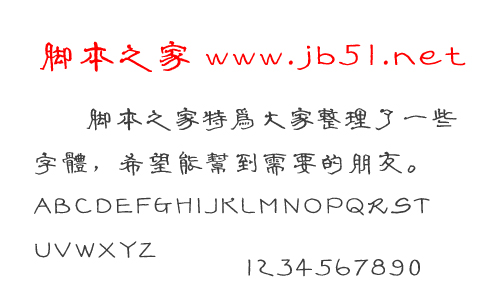
騰祥铚謙隸書繁是作者高铚謙先生撰寫的書法體字庫,整幅字體風格統(tǒng)一、行文規(guī)整,以清朝隸書大家的書法風格為創(chuàng)作源泉,以夸張的撇畫為突破口,從而使古老的隸書賦予時代的精神風范。灑脫飄逸的點畫、靈變的結體,唯美的字形、讓此字表現(xiàn)出獨有的個性魅力,本作品可用于出版印刷、廣告設計、網頁設計、包裝設計。歡迎喜歡騰祥铚謙隸書繁的朋友前來下載使用。